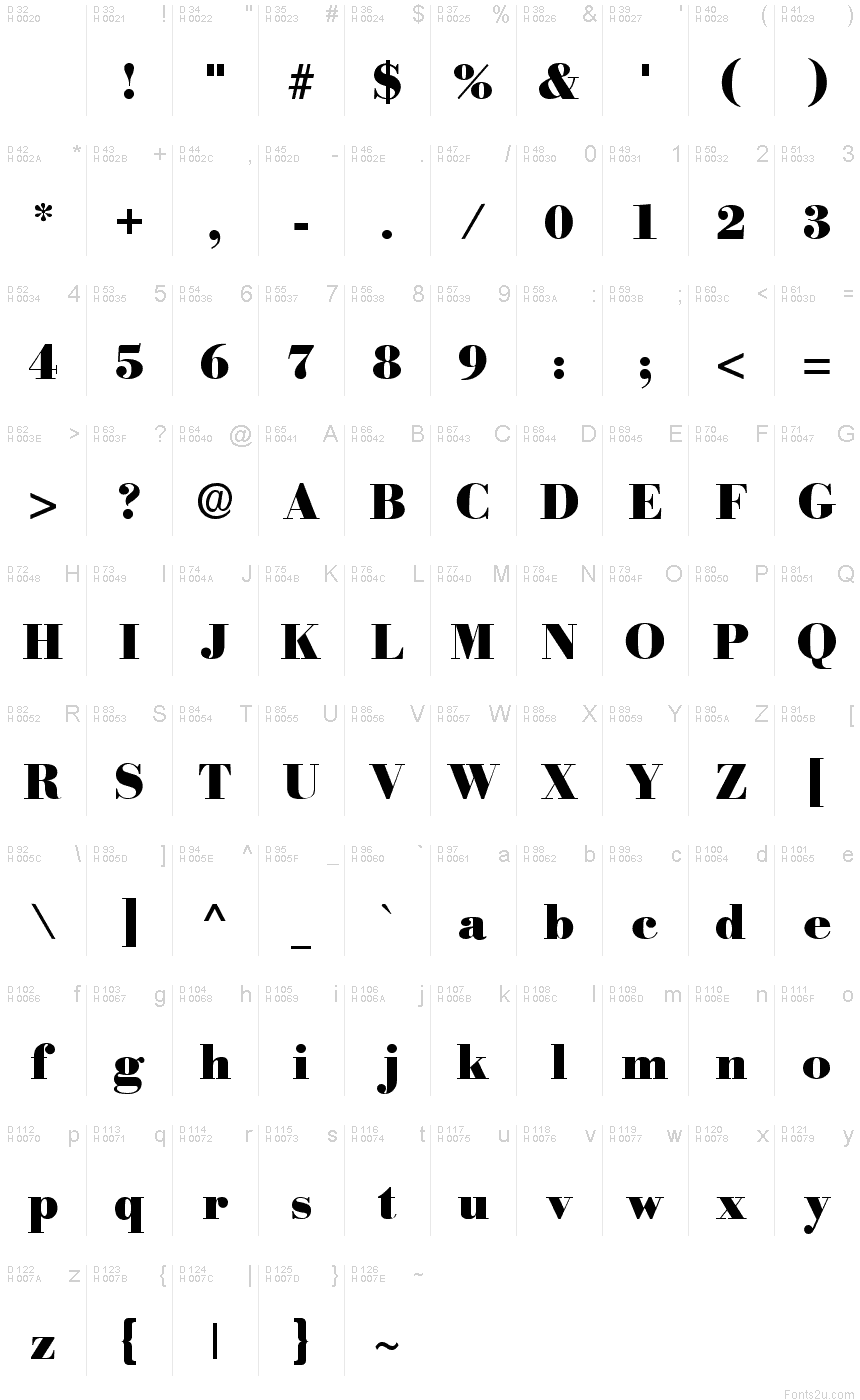
Poster to bezpłatny, szeryfowy krój pisma o wysokim kontraście, utrzymany w stylistyce klasycznych plakatowych nagłówków. Litery łączą w sobie ciężkie, masywne formy z ostrymi, cienkimi liniami i kompaktowymi szeryfami. Dzięki temu font wydaje się na pierwszy rzut oka formalny, ale z bliska urzeka subtelną, nieco ekscentryczną dynamiką krzywizn.
Idealnie pasuje do nagłówków w czasopismach, okładek książek, afiszy teatralnych, zaproszeń czy opakowań – wszędzie tam, gdzie darmowy font ma nadać krótkiemu tekstowi szczyptę dramaturgii w dawnym stylu. Wykorzystaj go w tytułach, okładkach lub dużych cytatach, gdy szukasz czegoś dostojnego, co jednocześnie wyróżnia się wyjątkowym detalem.